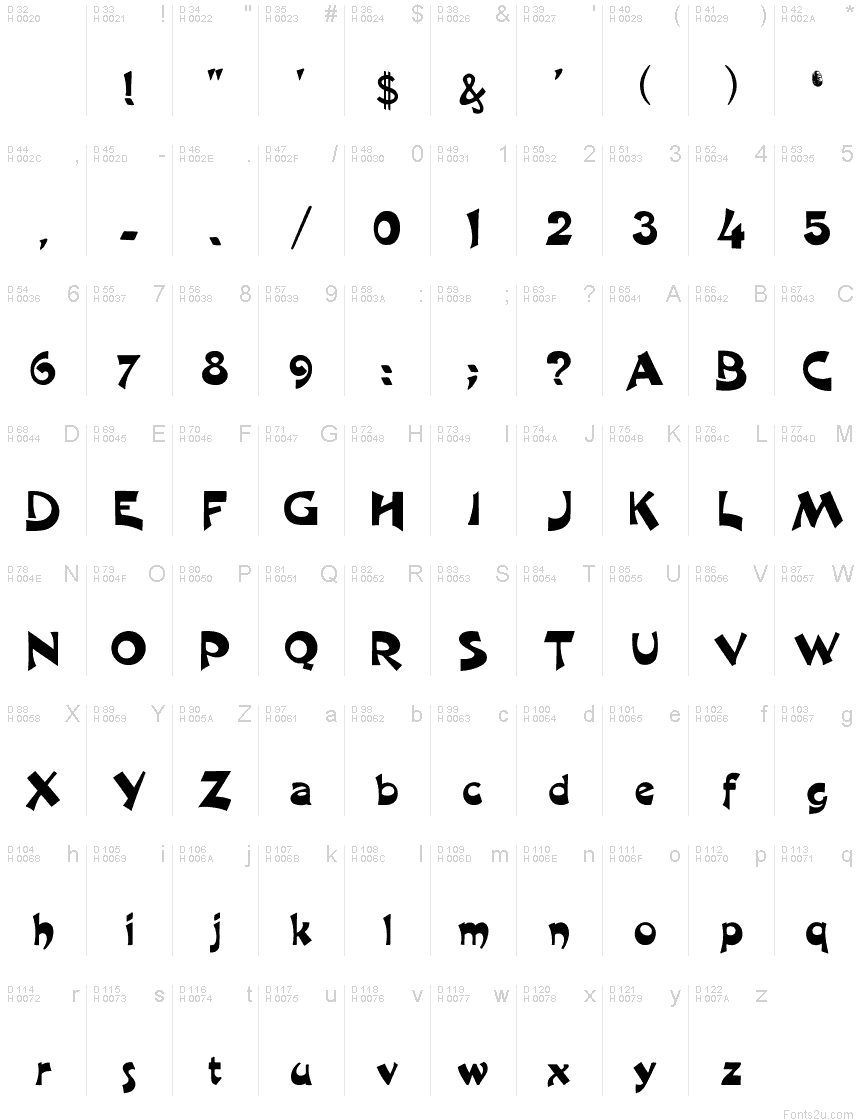
Harlequin od Dixie's Delights to darmowy krój pisma typu comic display, który wnosi do Twoich projektów zawadiacki uśmiech. Jego masywne, nieregularne pociągnięcia i zabawne, zygzakowate krawędzie wyglądają jak wycięte ręcznie z papieru litery, naklejone na plakat. Znaki chwieją się dokładnie tak, by sprawiać wrażenie psotnych, ale ich pogrubiona forma zapewnia czytelność nawet przy szybkim spojrzeniu.
Dzięki Harlequin Twoje nagłówki zyskają energię cyrkowego namiotu, co świetnie sprawdzi się na okładkach książek dla dzieci, zaproszeniach, plakatach karnawałowych, ulotkach na Halloween, tytułach gier czy w nieszablonowym brandingu. Ten darmowy font najlepiej prezentuje się w dużym rozmiarze, gdy ma przestrzeń, by wybrzmieć; w tekście głównym połącz go z czystym krojem bezszeryfowym, aby utrzymać zabawny charakter w ryzach.